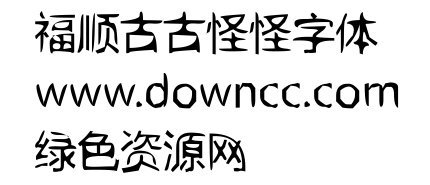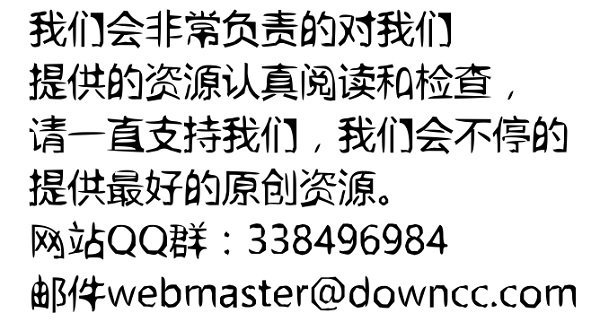
福順古古怪怪
福順古古怪怪字體是一款有著明顯加黑設(shè)計(jì)的福順字體,在每個(gè)漢字中都有不同程度的加粗部分,讓字體更加醒目易于閱讀,喜歡的朋友就來(lái)綠色資源網(wǎng)搶先體驗(yàn)吧!
古古怪怪字體特色
福順系列字體均有著與眾不同的設(shè)計(jì),或夸張或精簡(jiǎn),讓文字有了不一樣的呈現(xiàn),增加更加獨(dú)特的藝術(shù)效果體驗(yàn),而古古怪怪字體,讓中英文的書寫都變得不同尋常,藝術(shù)效果十分出色。
古古怪怪體,自如起名,中文變得更有棱角,英文卻在圓潤(rùn)中增加了集合構(gòu)造,打破常規(guī)的輸入體驗(yàn),可以廣泛運(yùn)用在藝術(shù)設(shè)計(jì)、平面設(shè)計(jì)等多種場(chǎng)合。